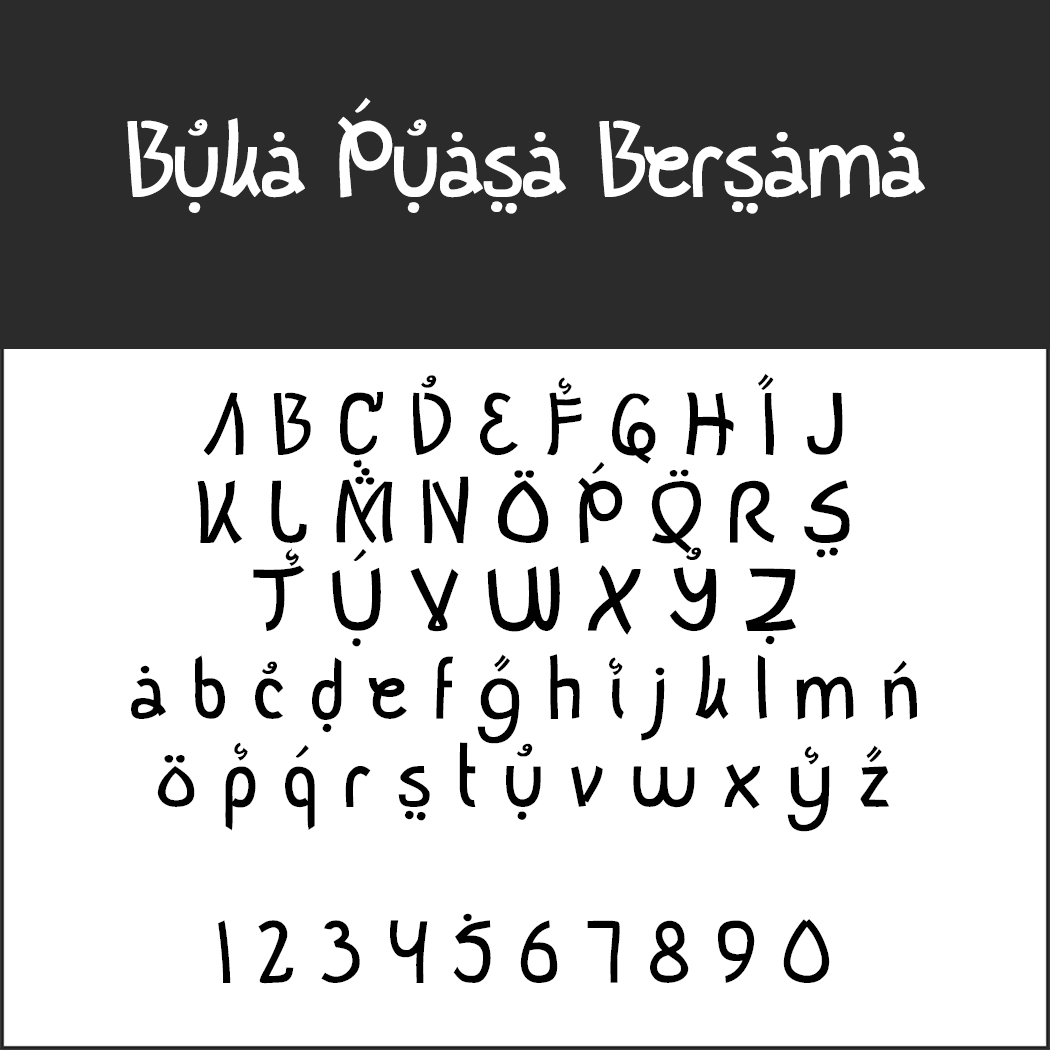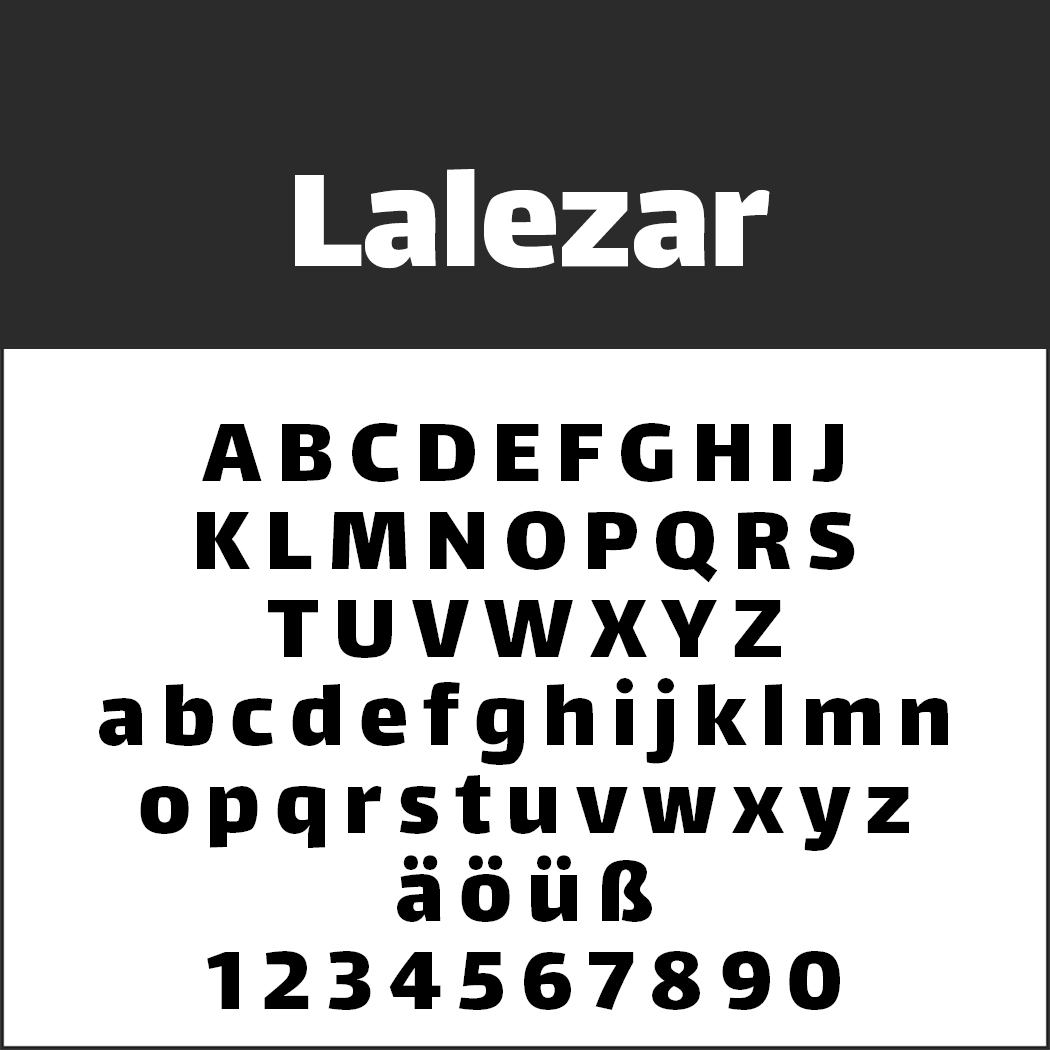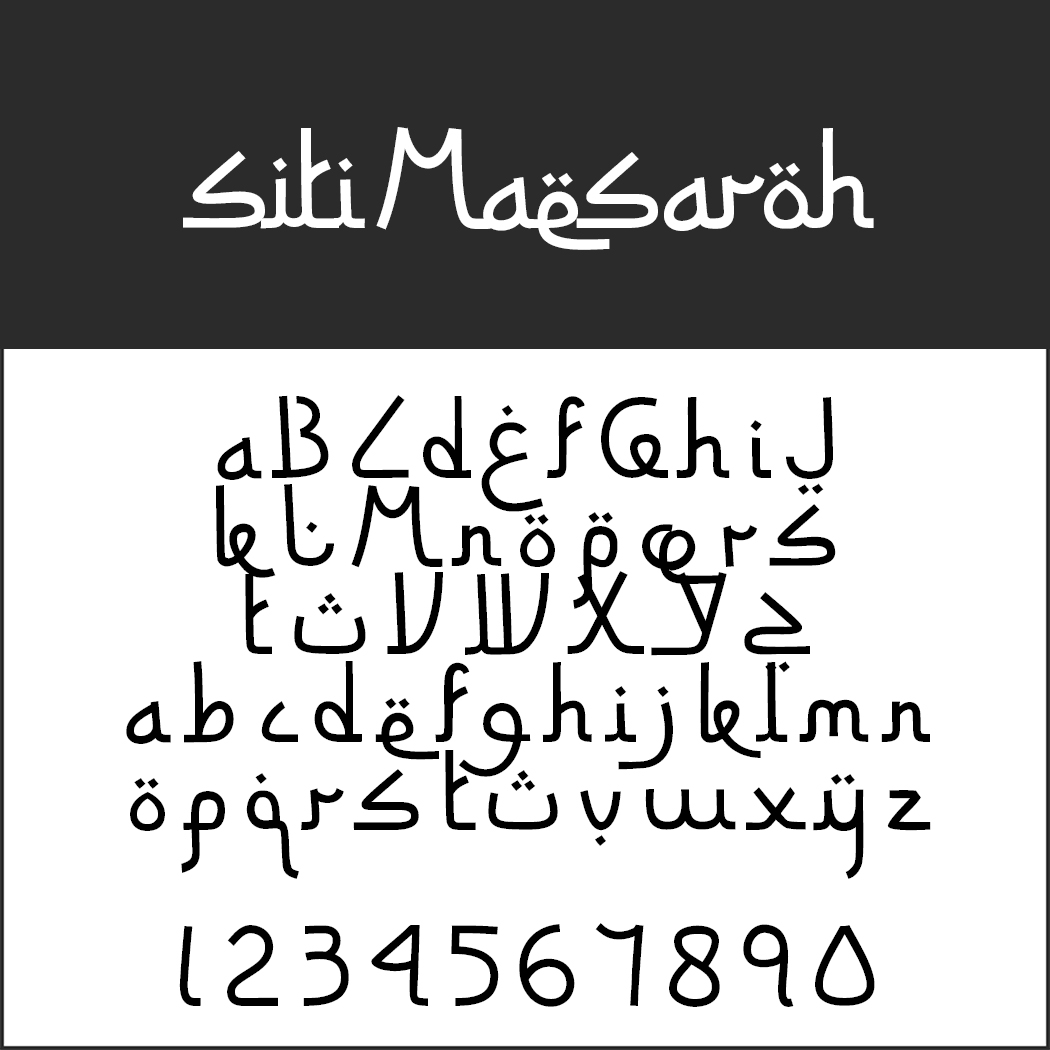
Arabische Schriftarten
Eines gleich vorweg: Sie finden hier keine echten arabischen Schriftarten, da wir diese wegen der Schreibrichtung von rechts nach links technisch nicht umsetzen können. Vielmehr stellen wir Ihnen Fonts vor, die durch raffinierte Details augenblicklich Assoziationen mit dem Orient wecken. Darunter befinden sich nicht nur arabische, sondern auch persische Anleihen.
Arabische Schriftarten für den besonderen Flair
El Messiri
Der moderne arabische Font erinnert mit seinen eleganten Abschwüngen an Naskh-Kalligrafie.
Arabisch aussehende SchnörkelschriftCatharsis Bedouin
Das mitteleuropäische Auge signalisiert auf den ersten Blick „nicht lesbar“ an das Gehirn. Tatsächlich handelt es sich aber um lateinische Buchstaben in nur eben sehr orientalischer Aufmachung. Wir können es also lesen, wenn auch mit großer Anstrengung .
Schriftart Markazi Text
Der Font orientiert sich an Tim Holloways Markazi Font. Einige Details der arabischen Variante finden sich auch in der Ausgestaltung der lateinischen Buchstaben.
Font LalezarLalezar
In den 1960er und 1970er Jahren waren im Iran schrille Kinostreifen angesagt, der sogenannte Farsi-Film. Lalezar imitiert mit arabischen und lateinischen Buchstaben den ganz eigenen Stil der damaligen Filmplakate.
Eine Hommage an die kluge, Geschichten erzählende Scheherazade: ein moderner Font mit Anleihen der Monotype Naskh.Scheherazade
Eine Hommage an die kluge, Geschichten erzählende Scheherazade: ein moderner Font mit Anleihen der Monotype Naskh.
Arabisch aussehende SchriftBuka Puasa Bersama
Der Designer bringt mit seinem Font typische Elemente arabischer Schriften in lateinischen Buchstaben.
Arabisch anmutender Font Ceria Lebaran (keine echte arabische Schriftart)Ceria Lebaran
Bei diesem Font denken wir sofort an Falafel und andere Köstlichkeiten aus dem Nahen Osten. Ceria Leabaran empfiehlt sich daher vor allem für kulinarische Angebote.
Schriftart mit fernöstlichem FlairSiti Maesaroh
Leicht und unbekümmert springen die Buchstaben in diesem Font mit fernöstlichem Flair. Nicht geeignet für Fließtexte, aber ein Hingucker in Überschriften.
Arabisches SchriftbildAceh Darusalam
Wirklich schwer lesbar, aber mit arabisch-atmosphärischer Stimmung kommt dieser Font für alles infrage, was sich auf den Nahen Osten bezieht.
Arabische Schriftarten (hier Tafakur, arabisch anmutend, keine echte arabische Schrift))Tafakur
Exotisch und geheimnisvoll gibt sich Tafakur, das vom Font Alpha Kufi von Agung Yuwanda beeinflusst ist.
Schriftart Sinbad the Sailor
Hier haben wir einen weiteren Helden aus Tausendundeiner Nacht. Der auf Linie gebrachte Font ist vor allem für aufmerksamkeitsstarke Überschriften gedacht.
Arabisch anmutende Schriftart (keine echte arabische Schriftart)
Assyrian
Für Plakate und andere großflächige Präsentationen geeignet: Assyrian gibt es in vier Schriftschnitten, zum Teil mit schönen 3D-Effekten.